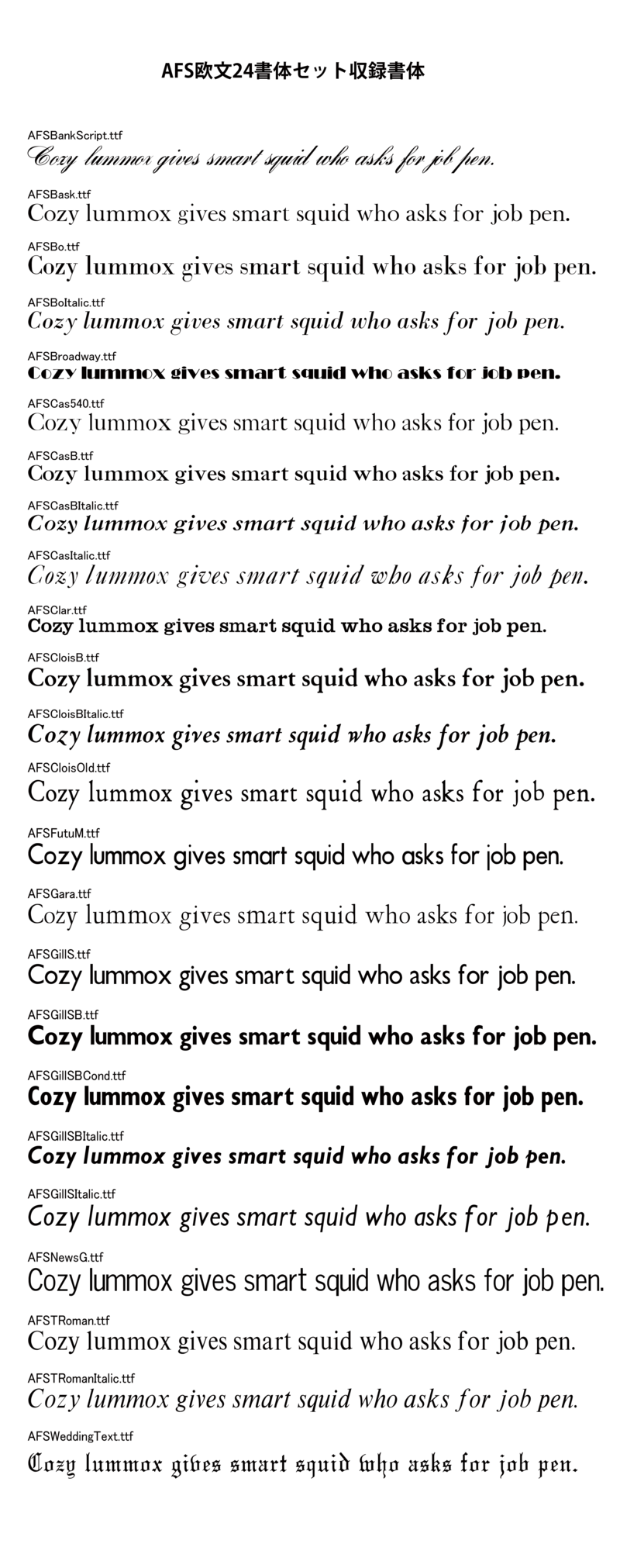
※復刻のため記号類に不足がございます。詳細はこちらをご確認ください。
「AFS欧文24書体セット」は歴史的な活字印刷からトレースしたデジタルフォント24書体を収録しています。収録書体の詳細はギャラリーをご確認ください。
※プレビューフォントはAFSBankScriptです。
AFS欧文24書体セット